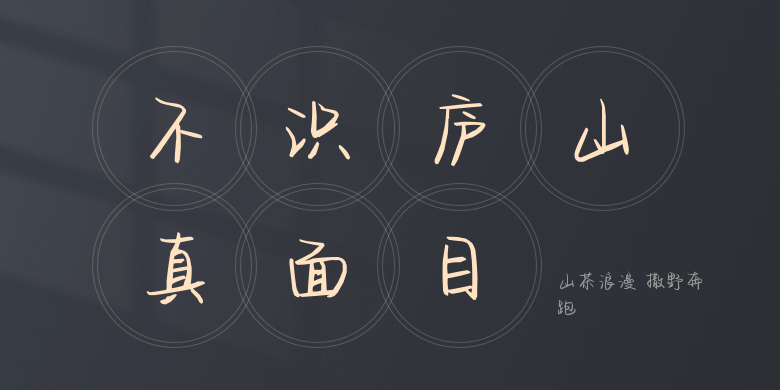
山茶浪漫 撒野奔跑
山茶浪漫 撒野奔跑,这款字体结构工整、笔画清晰,兼顾美观与易读性,适用于标题、正文、海报、包装、LOGO 等多种场景。字形优雅稳定,风格百搭耐看,适配日常排版与创意设计,让文字呈现更舒适、更具质感。山茶浪漫 撒野奔跑一笔一画,皆是细节,以均衡的比例、流畅的线条打造舒适视觉体验,字形端正大气,风格简约现代。无论是商业设计、品牌宣传还是日常排版,都能轻松驾驭,让文字更有格调与力量。山茶浪漫 撒野奔跑字体下载。